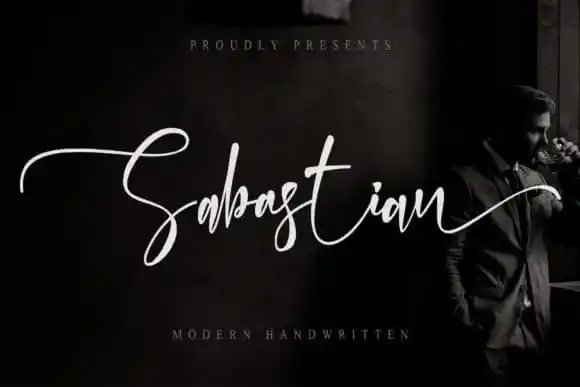
Sabastian Script Font – Download Grátis
A “Sabastian Script Font” é uma nova opção que traz estilo moderno para sua próxima criação visual. Esta fonte tem um encanto autêntico e delicado, inspirada em técnicas de escritura manual e com detalhes decorativos, criando um aspecto quase dançante na linha base. Desenvolvida pelo designer Thomas Aradea, a “Sabastian Script Font” combina perfeitamente estilos antiquados com uma versatilidade moderna, tornando-a ideal para qualquer tipo de projeto gráfico. O fato de ser PUA (Propriedade Unificada) encoded permite que você facilmente abraça todos os encantos únicos e detalhes exuberantes da fonte. Adicionalmente, a fonte oferece uma variedade de características especiais: alternativas de letras para adicionar flexibilidade ao texto, e ligaduras para garantir uma estética perfeita nos textos mais complexos. A “Sabastian Script Font” é uma escolha inteligente que adicionará um toque especial a qualquer design, oferecendo tanto estilo quanto versatilidade.